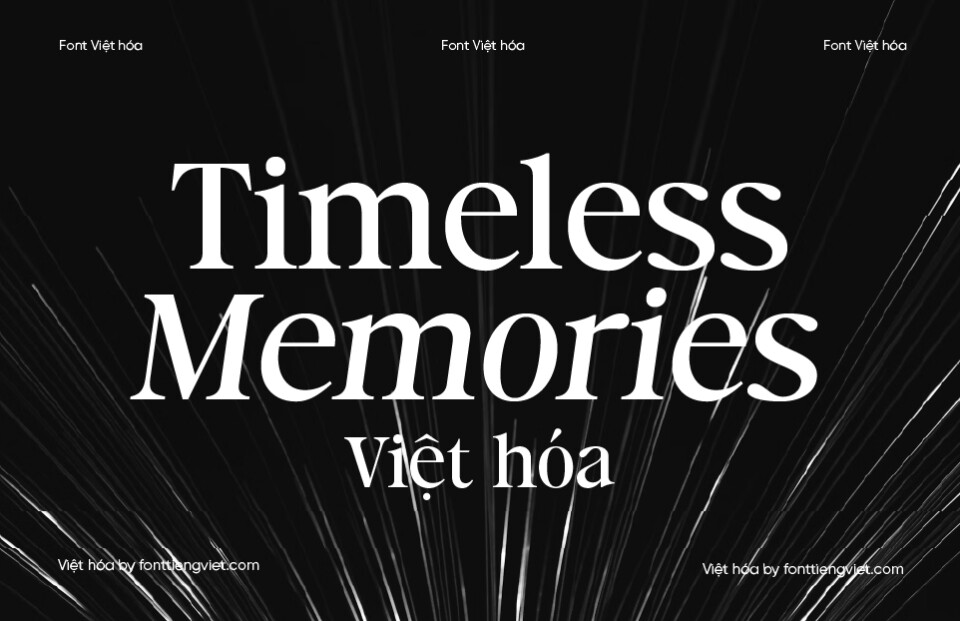
Font Việt hóa 1FTV VIP Timeless Memories Regular
Font Việt hóa 1FTV VIP Timeless Memories Regular – Nghệ thuật lưu giữ kỷ niệm qua từng nét chữ
Trong thế giới thiết kế đồ họa hiện đại, việc lựa chọn một bộ Font Miễn Phí chất lượng đóng vai trò quan trọng trong việc truyền tải cảm xúc. Font Việt hóa 1FTV VIP Timeless Memories Regular nổi lên như một sự lựa chọn hoàn hảo dành cho những ai đang tìm kiếm sự hoài niệm và sang trọng. Đây không chỉ là một phông chữ thông thường mà còn là công cụ đắc lực giúp các nhà thiết kế tạo nên những tác phẩm nghệ thuật mang đậm dấu ấn cá nhân và hơi thở của thời đại. Với khả năng hỗ trợ tiếng Việt hoàn chỉnh, bộ font này loại bỏ hoàn toàn nỗi lo lỗi font khi gõ dấu, mang lại trải nghiệm mượt mà nhất cho người dùng.
Đặc điểm nổi bật của Font Việt hóa 1FTV VIP Timeless Memories Regular
Thiết kế thanh lịch và tinh tế
Đúng như tên gọi của mình, Font Việt hóa 1FTV VIP Timeless Memories Regular mang trong mình vẻ đẹp của những kỷ niệm vượt thời gian. Các đường nét được trau chuốt tỉ mỉ, kết hợp giữa sự cổ điển và hiện đại một cách khéo léo. Cấu trúc chữ cái có độ tương phản nhẹ nhàng, tạo cảm giác dễ đọc nhưng vẫn giữ được sự bay bổng cần thiết. Điều này giúp bộ font trở nên cực kỳ linh hoạt, phù hợp với nhiều loại dự án khác nhau từ trang trọng đến gần gũi.
Khả năng tương thích và ứng dụng đa dạng
Phiên bản Regular này được tối ưu hóa để hiển thị tốt trên cả nền tảng kỹ thuật số và in ấn. Cho dù bạn đang thiết kế một tấm thiệp mời đám cưới, bìa sách, hay tiêu đề cho một trang blog cá nhân, Font Việt hóa 1FTV VIP Timeless Memories Regular đều có thể đáp ứng tốt yêu cầu về thẩm mỹ. Đặc biệt, bộ font này rất được ưa chuộng trong các thiết kế mang phong cách vintage hoặc retro, nơi mà yếu tố cảm xúc được đặt lên hàng đầu.
Cách sử dụng Font Việt hóa 1FTV VIP Timeless Memories Regular hiệu quả
Kết hợp với các yếu tố hình ảnh
Để phát huy tối đa vẻ đẹp của font chữ này, bạn nên kết hợp nó với những tông màu trung tính hoặc các họa tiết mang phong cách cổ xưa. Một bức ảnh phong cảnh nhuốm màu thời gian đi kèm với dòng chữ được viết bằng Font Việt hóa 1FTV VIP Timeless Memories Regular chắc chắn sẽ tạo nên một sức hút khó cưỡng. Đừng quên chú ý đến khoảng cách giữa các chữ cái (kerning) để đảm bảo sự cân đối tổng thể cho bố cục thiết kế của bạn.
Lựa chọn cho các dự án giáo dục và học đường
Với phong cách rõ ràng và dễ tiếp cận, các em học sinh và thầy cô giáo cũng có thể sử dụng bộ font này trong các bài thuyết trình hoặc làm báo tường. Nó giúp nội dung trở nên sinh động hơn, không bị khô khan như các font hệ thống thông thường. Việc sử dụng font chữ đẹp còn góp phần khơi gợi niềm đam mê sáng tạo trong học tập và giảng dạy hàng ngày.
Tổng kết về bộ Font Việt hóa 1FTV VIP Timeless Memories Regular